8月17日,从广大影迷中传来一个悲伤的消息:年轻的字体设计师尚巍因车祸意外不幸去世,他曾为《我不是药神》《哪吒之魔童降世》《白日焰火》等影视作品进行字体创作。
8月16日,尚巍工作室在微博发布讣告
8月16日,尚巍工作室官方微博 @笔染时光 发布讣告称:“尚巍先生于2021年7月11日,因车祸意外不幸去世,现已返回家中发丧安葬。”
据悉,尚巍创作的“汉仪尚巍手书”等多个手写字体被广泛使用。《我不是药神》《哪吒之魔童降世》《无名之辈》等多部影视剧都曾用过他的字体。
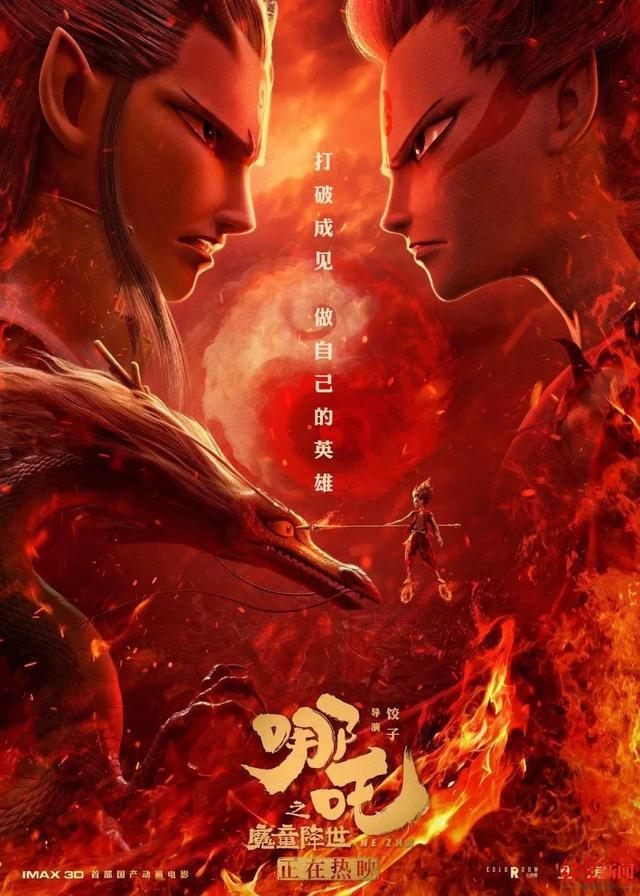
《哪吒之魔童降世》海报上有尚巍的字体图据片方
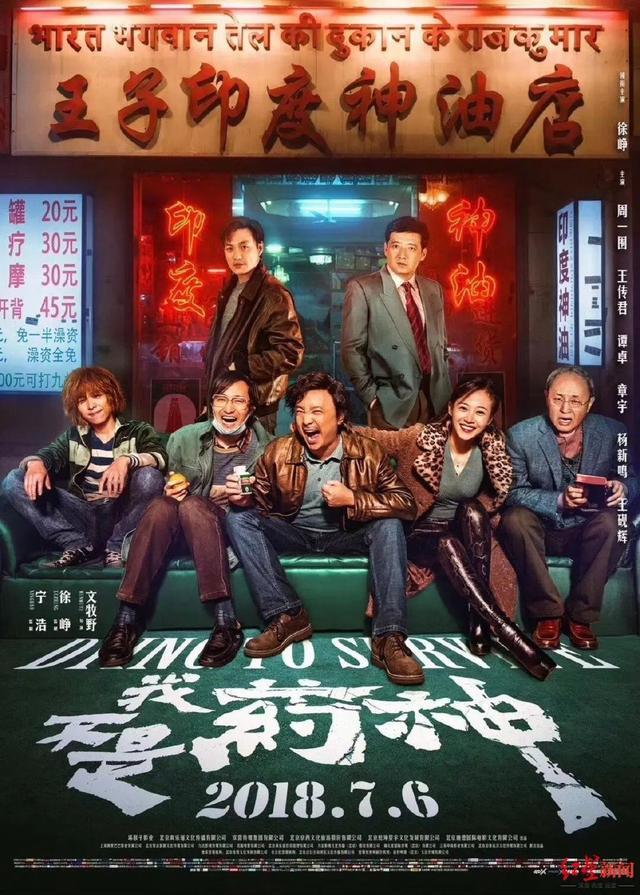
《我不是药神》海报上有尚巍的字体图据片方
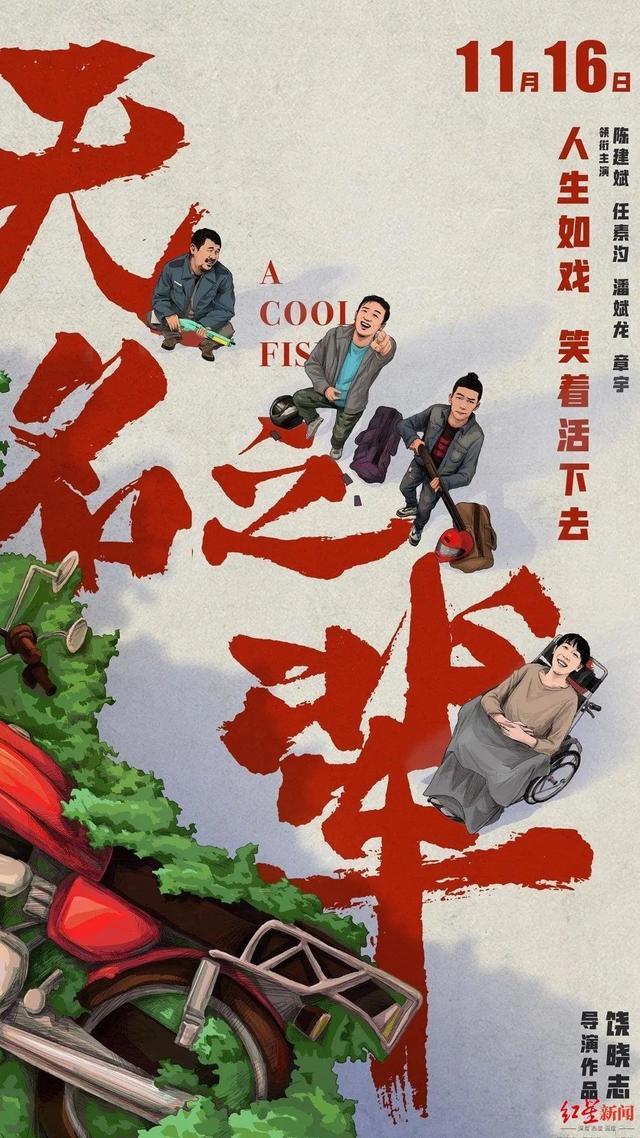
《无名之辈》海报上有尚巍的字体图据片方
此外,尚巍在微博发布的《写给妈妈的二十一封信》曾感动不少网友。
尚巍在微博发布的《写给妈妈的二十一封信》
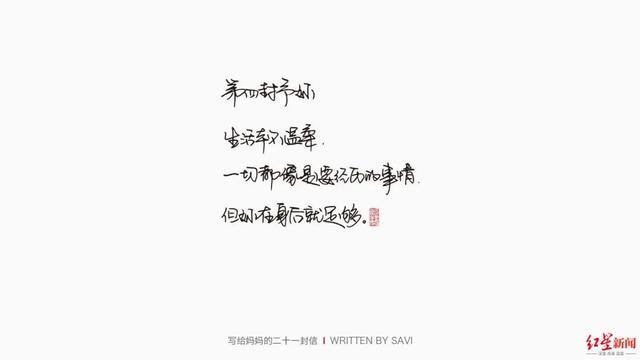
尚巍在微博发布的《写给妈妈的二十一封信》
今年4月12日,尚巍发微博写道:“我今年30岁了。如果你今年也30岁,不出意外的话,我们还可以吃40多次年夜饭,还能过1000多个周末,还能看10000多次日出……所以想做什么,现在就可以往前走了。时间扑面而来,我们终将释怀。”
“汉仪尚巍手书”,是尚巍在2016年10月份发布的字体包,与传统的规整字体不同,这款字体笔画张扬,极具个性。创作这款字体初始,尚巍刚刚裸辞离开设计公司,他跟自己说,“你什么都没有了,只能硬着头皮往前跑。”
尚巍曾在微博表示《哪吒之魔童降世》片头尾字幕是他写的尚巍手书
没有了设计,他还有一个技能,就是写字,当时在设计领域,大部分人设计字体是需要拿笔刷去拼字,他思考能不能出一套适合设计使用的,有表达温度的手写体字库呢?
他开始了“汉仪尚巍手书”的创作。一般来说,一套汉字字库的手稿制作,至少需要三到四个月的时间。而在一无所有,又极度想要证明自己的情况下,尚巍仅仅花了28天就完成了创作。
这28天里,他每天工作14个小时以上,报废4支毛笔,用尽3瓶500g的墨汁,右肩膀全部肿起,右手比左手整整大了一圈。